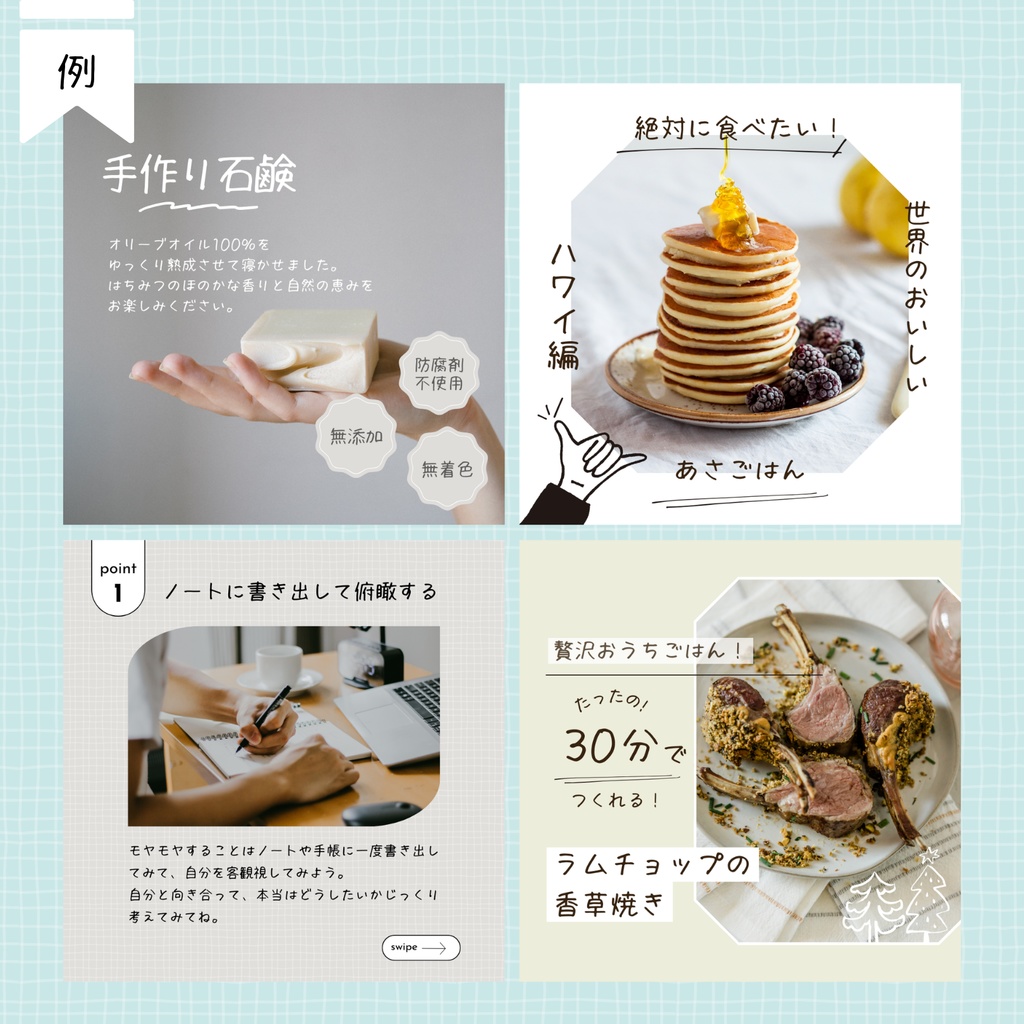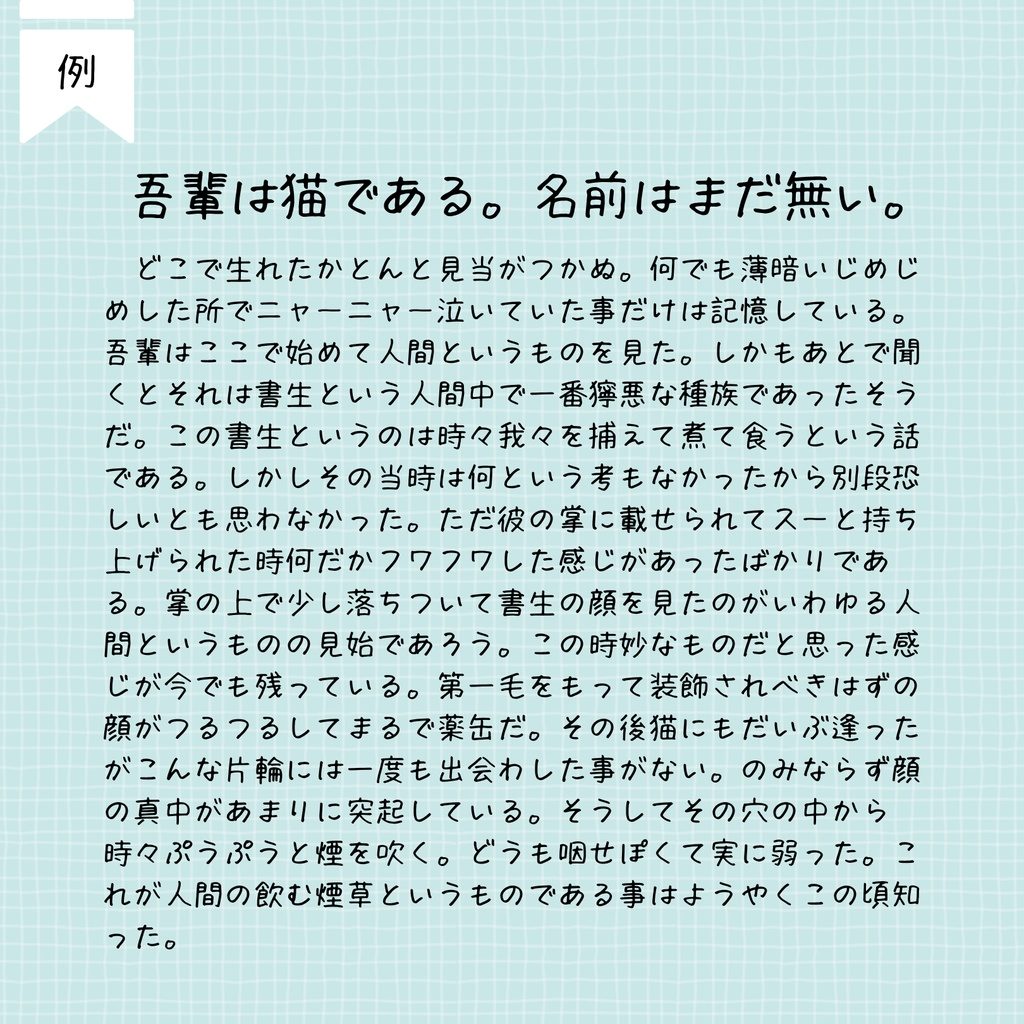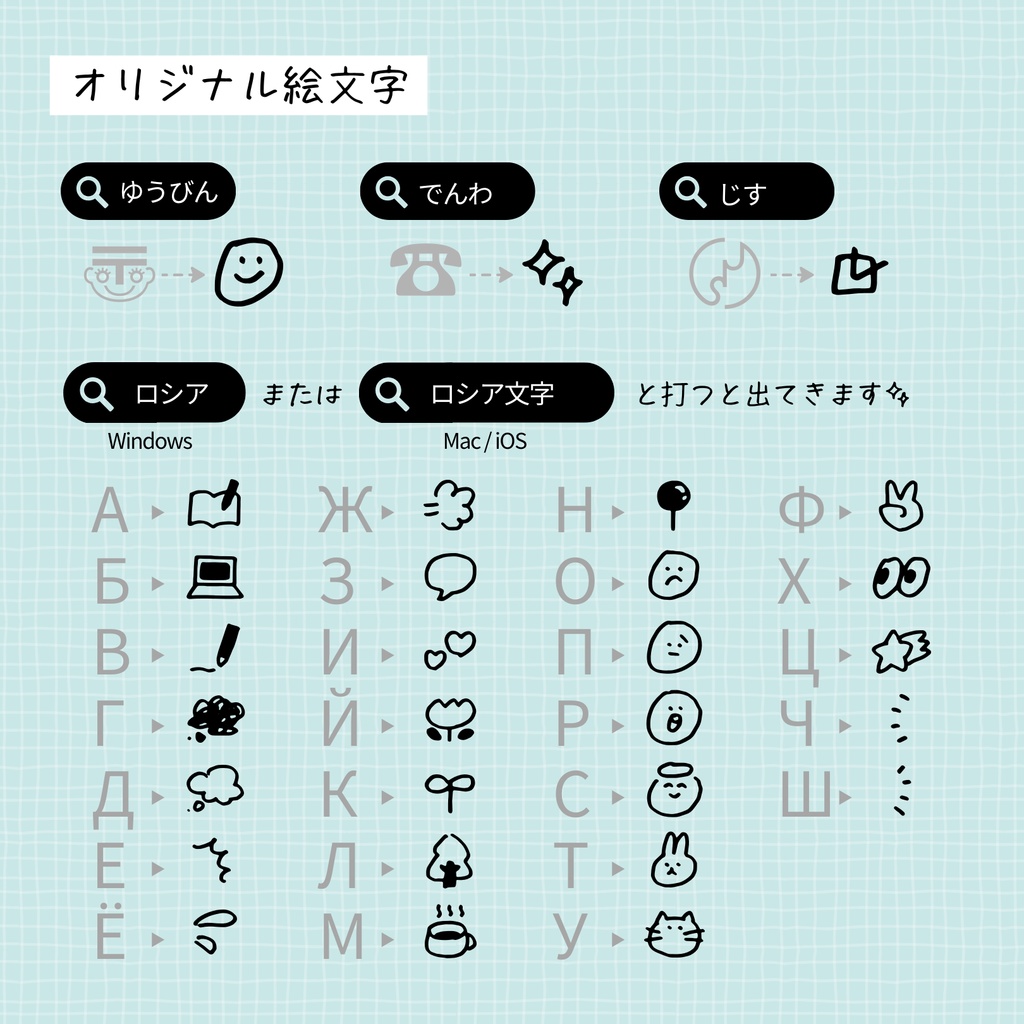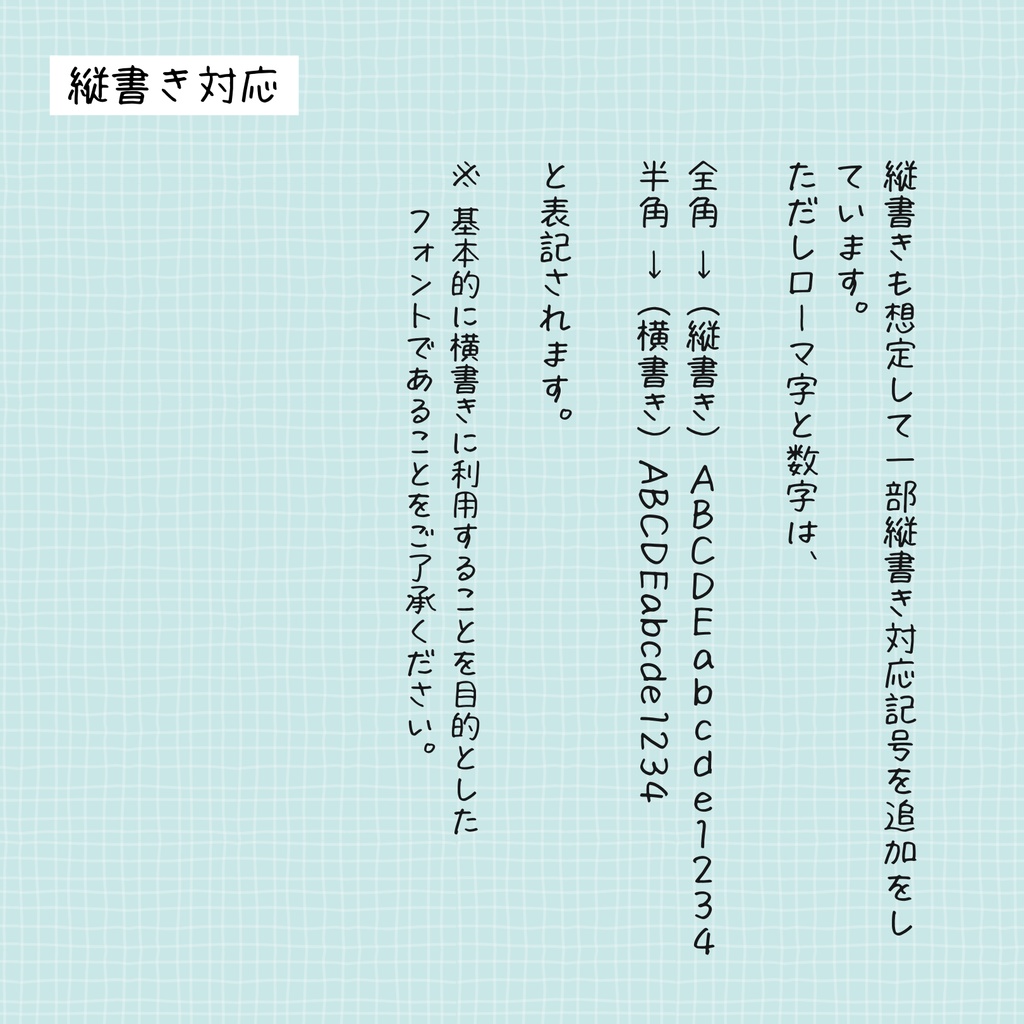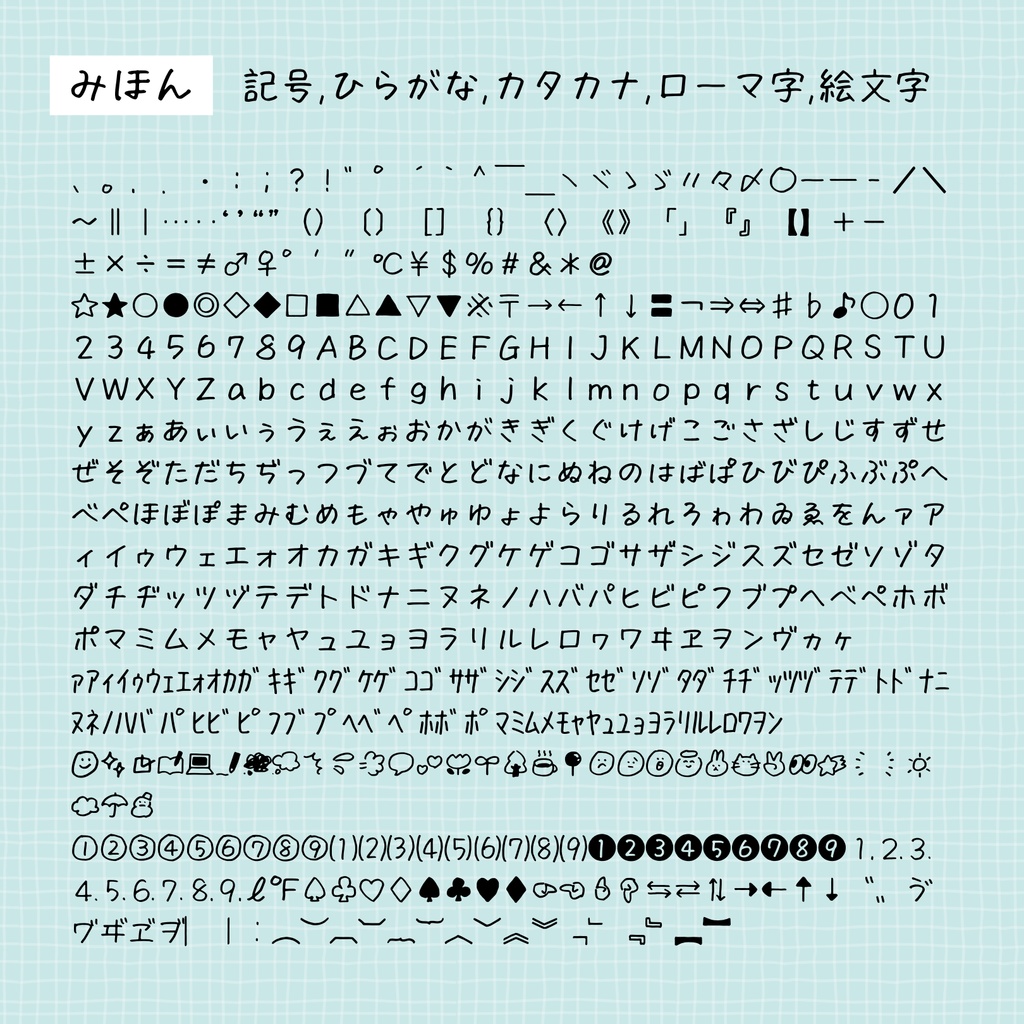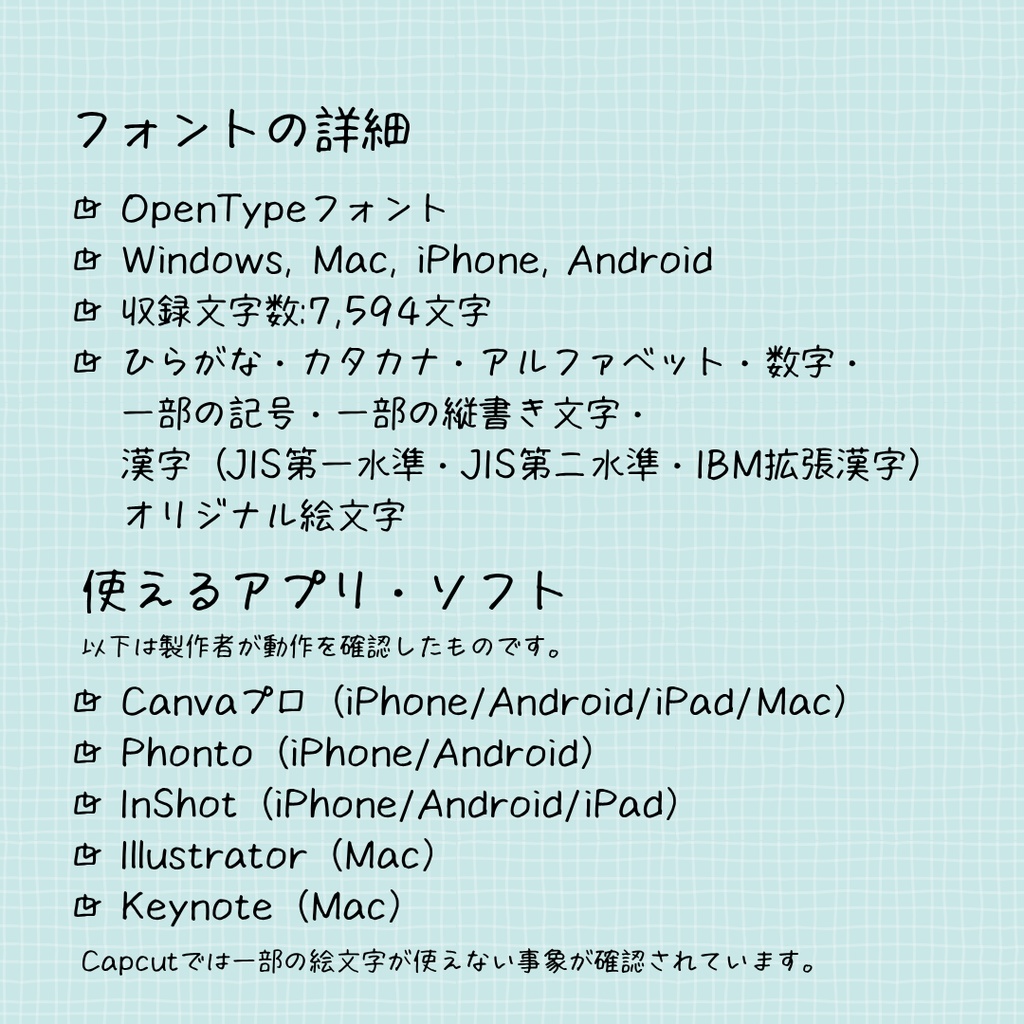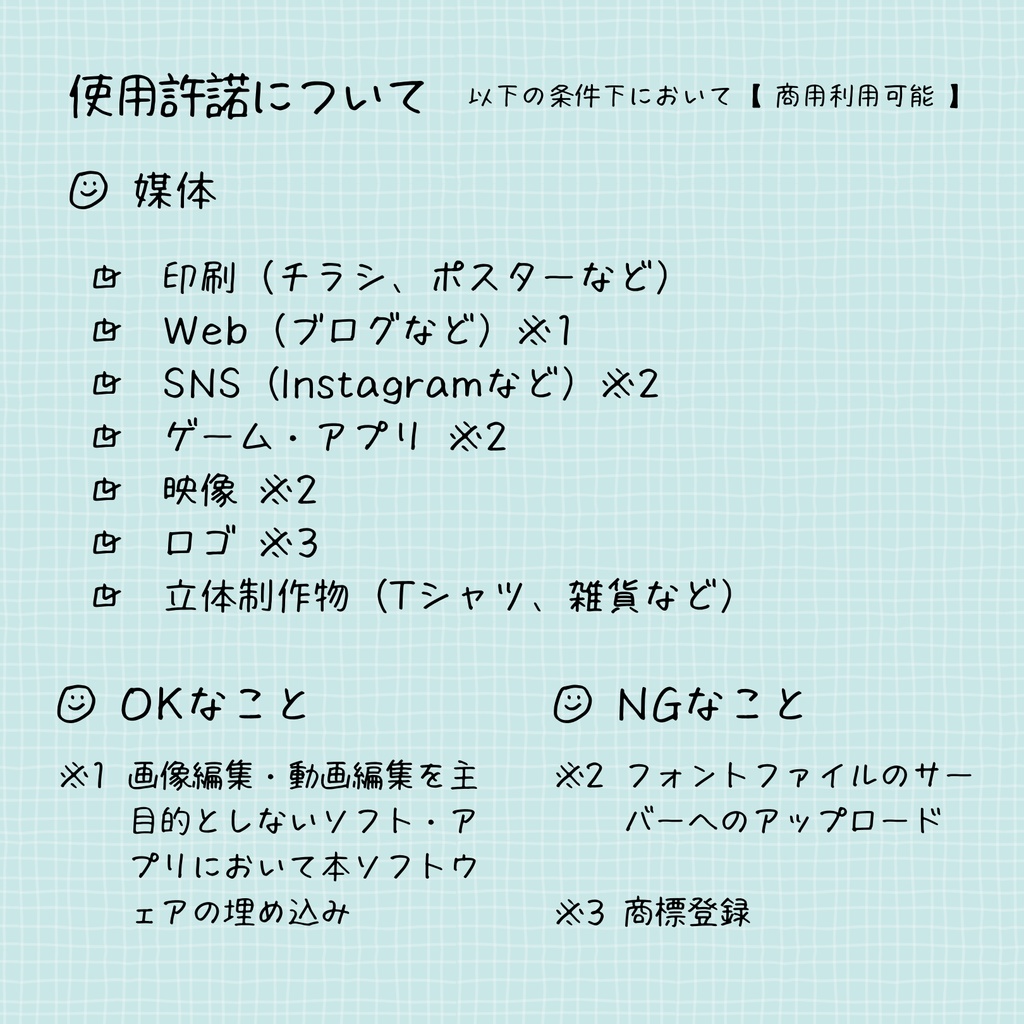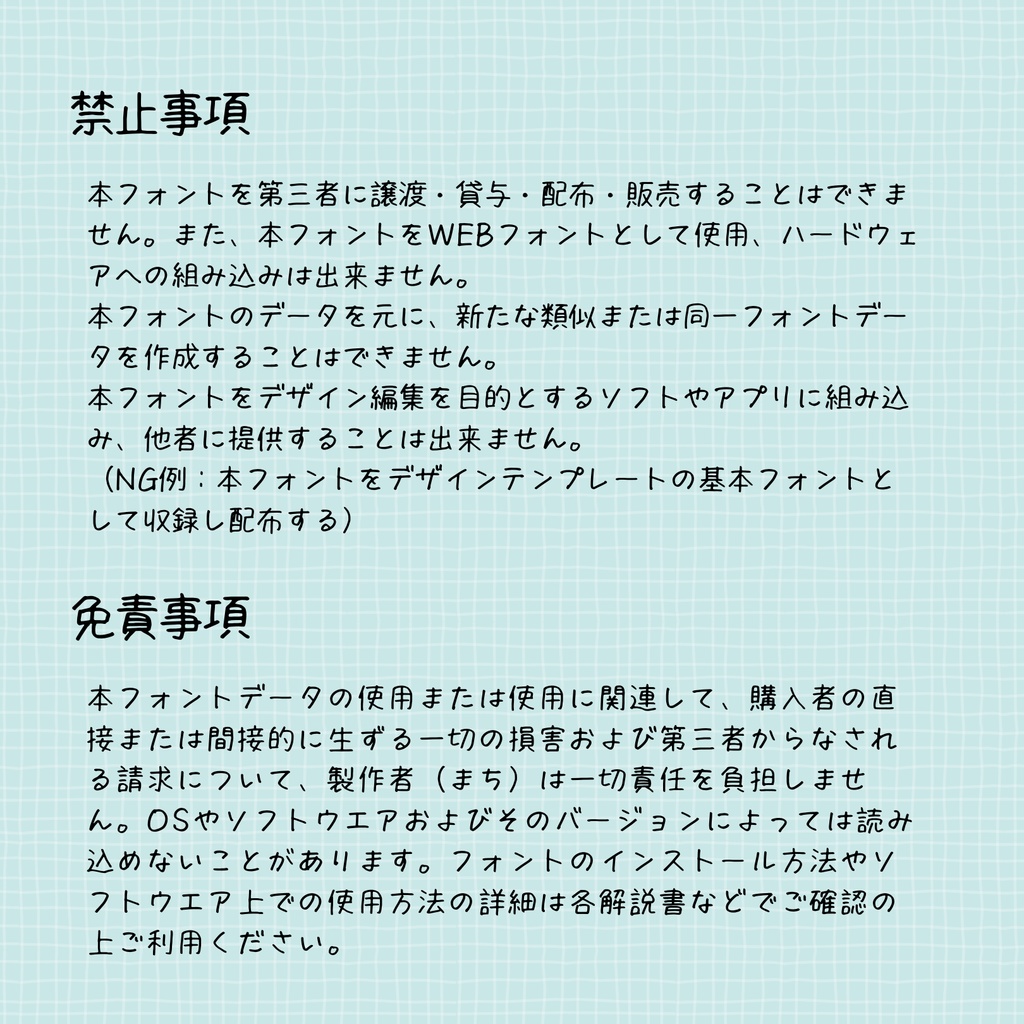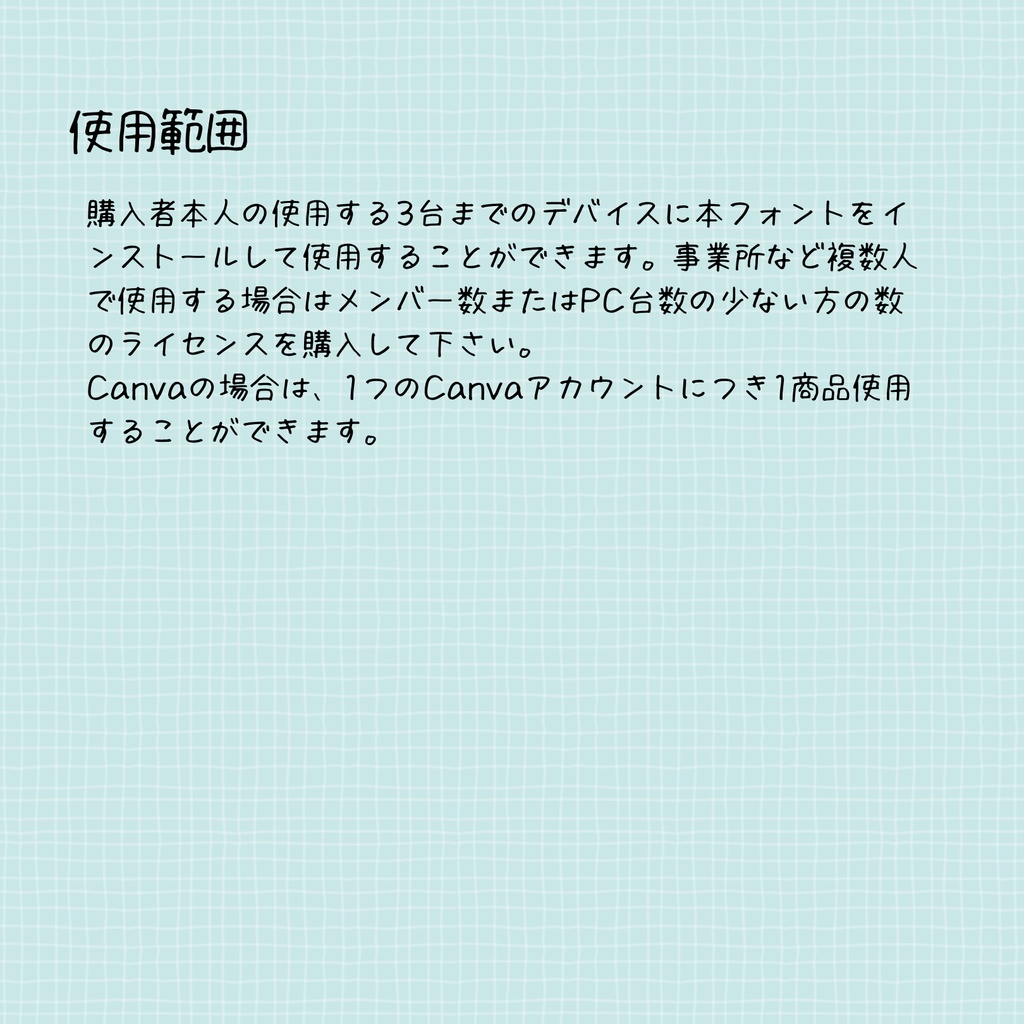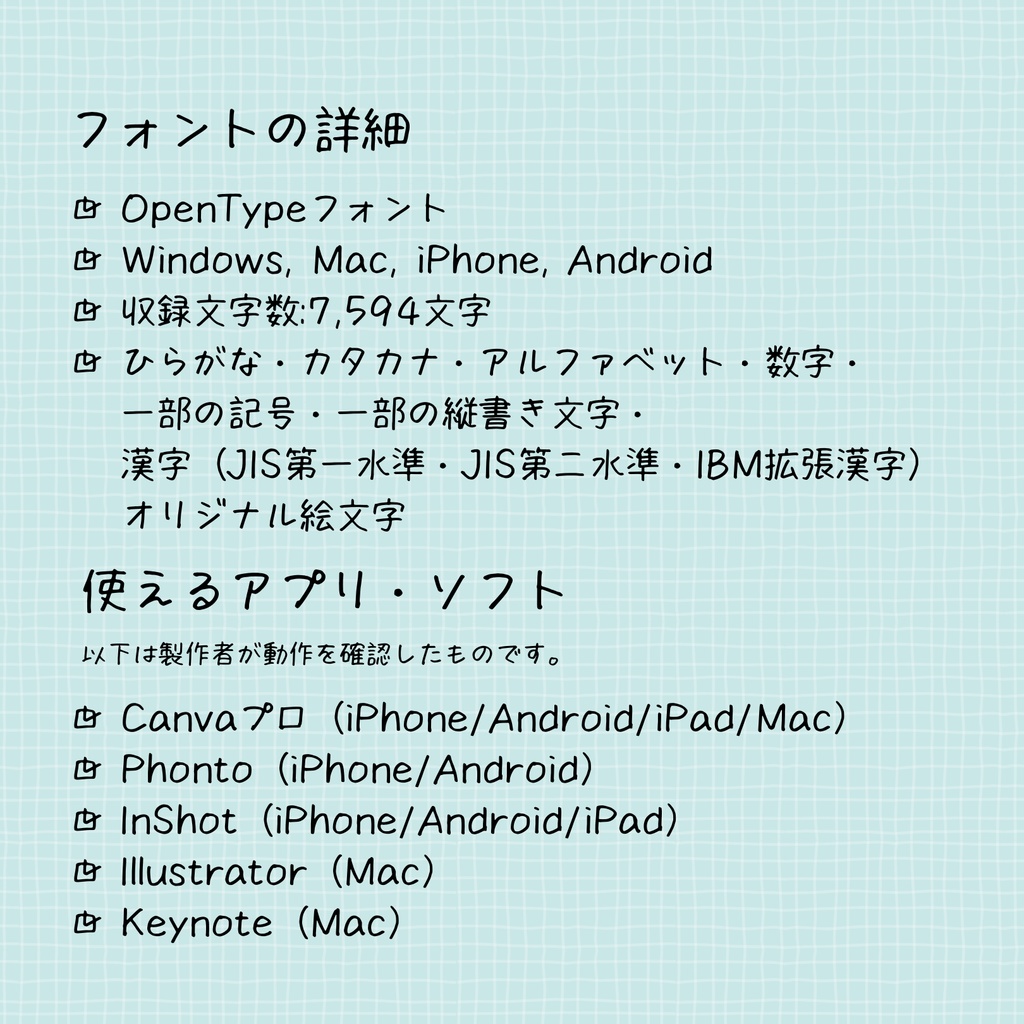
【商用利用可】手書きフォント「まちのらくがき」
iPadとApple Pencilを使用し、1文字ずつ直筆で作成しました。 漢字も幅広くカバーしておりますので、 日常的なSNSの画像作成、創作活動などにお役立てください。 製作者は主にCanvaプロ、Procreate、Illustratorでフォントを活用しています◎ 初めてフォントを取り扱う方のために、 フォントをダウンロードした後の使い方ページも作成しました。 https://temporal-roquefort-94b.notion.site/103e5264ce9a47cc8e708378907fa245?pvs=4 【注意】 購入前に、商品画像内の ・フォントの詳細 ・使えるアプリ・ソフト ・使用許諾について ・禁止事項 ・免責事項 ・使用範囲 についてご一読ください。 ◼︎◼︎◼︎お知らせ◼︎◼︎◼︎ (随時更新) ◼︎◼︎◼︎◼︎◼︎◼︎◼︎◼︎◼︎◼︎